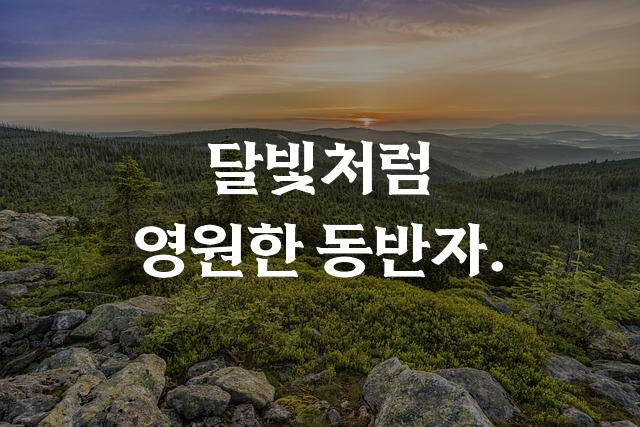
파셜산스는 둥글고 가로로 길게 늘어진 고딕 스타일의 폰트로, 레트로 감성이 묻어나는 장식체 디자인입니다. 제목용으로 적합하며, 동글동글한 특징이 친근감을 줍니다.
파셜산스은(는)
브랜딩, 로고 디자인 등에서 자주 활용되며, 효과적인 메시지 전달에 적합합니다.
이 폰트는 건축/인테리어, 패션/뷰티 분야에 잘 어울리며,
고급스러운, 세련된 느낌을 담고 있는 것이 특징입니다.